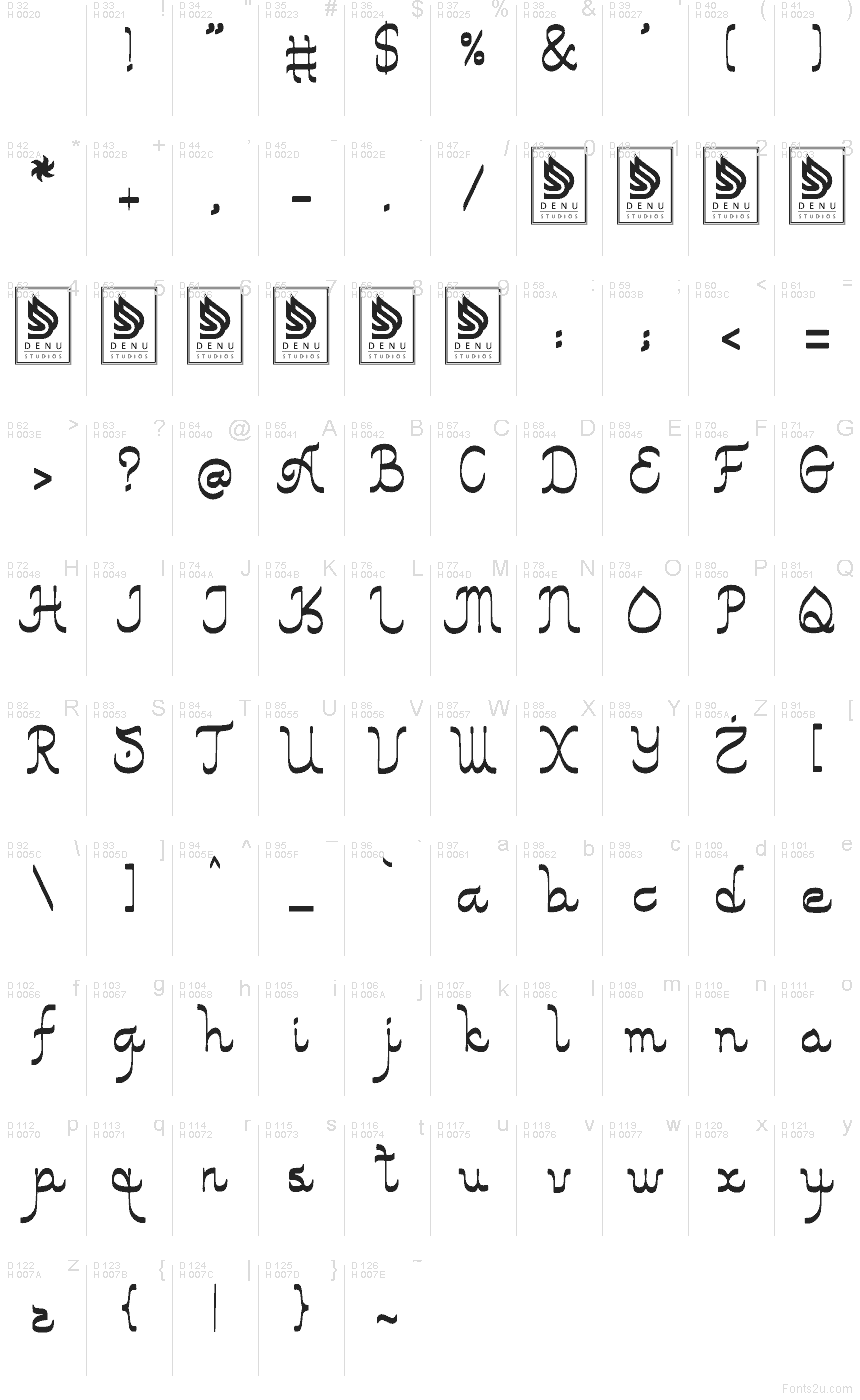
Al Hidayah, creada por Denustudios, es una tipografía display gratuita de estilo caligráfico árabe con trazos fluidos y un ritmo suave y conectado. Sus letras se apoyan en curvas amplias, uniones altas y remates en forma de gota, lo que le otorga un aire ornamental y artesanal que recuerda más al rótulo pintado a mano o al lettering estilizado que a un diseño de texto neutro.
Esto la convierte en una opción natural para branding, cartelería de cafeterías o boutiques, pósteres de eventos, packaging y portadas donde una sola palabra o una frase corta deba marcar el estilo. Al ser una fuente gratuita, Al Hidayah funciona especialmente bien en logotipos, tarjetas de presentación y monogramas, ya que sus uniones expansivas y giros redondeados aportan una silueta fuerte y continua incluso a textos muy breves.